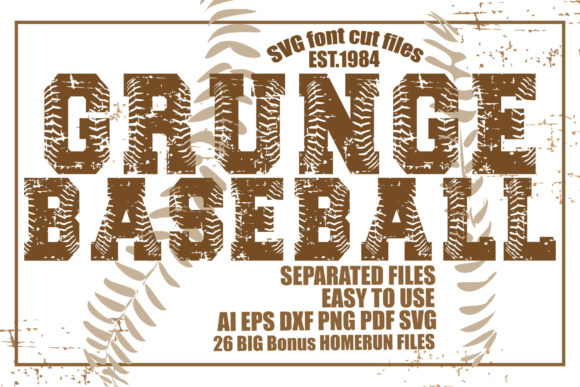
Grunge Baseball SVG Font Cut Files
Được chế tác với độ chính xác cao, Grunge Baseball SVG Font Cut Files cung cấp các vector sạch, kiểu chữ mượt mà và giấy phép thương mại để bạn yên tâm.